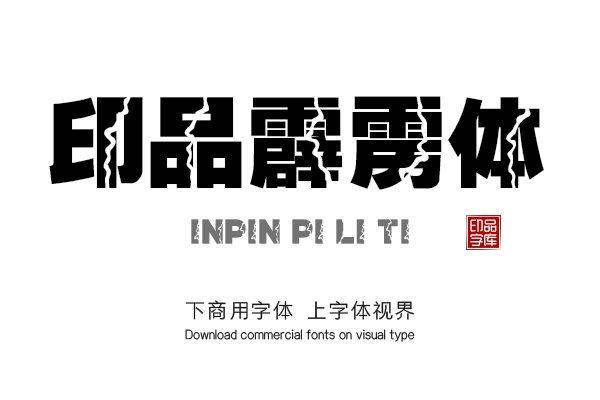
「印品霹雳体」一款稳重又富有创意的字体
整体结构基于超粗黑体的基本笔画特征,粗重浑厚。笔画之间生动变化,刻画出“列缺霹雳 丘峦崩摧”的震撼。字面饱满,结构稳重大方,更加醒目,极具现代感与个性化。
印品霹雳体
印品霹雳体是一款沉稳又颇具艺术创意的字体,厚重,喻蓄势于中心,错落有致,平稳和谐,展现通上彻下的能量释放。字形雄厚有劲,应景感极强,适用于广告创意设计。
印品霹雳体